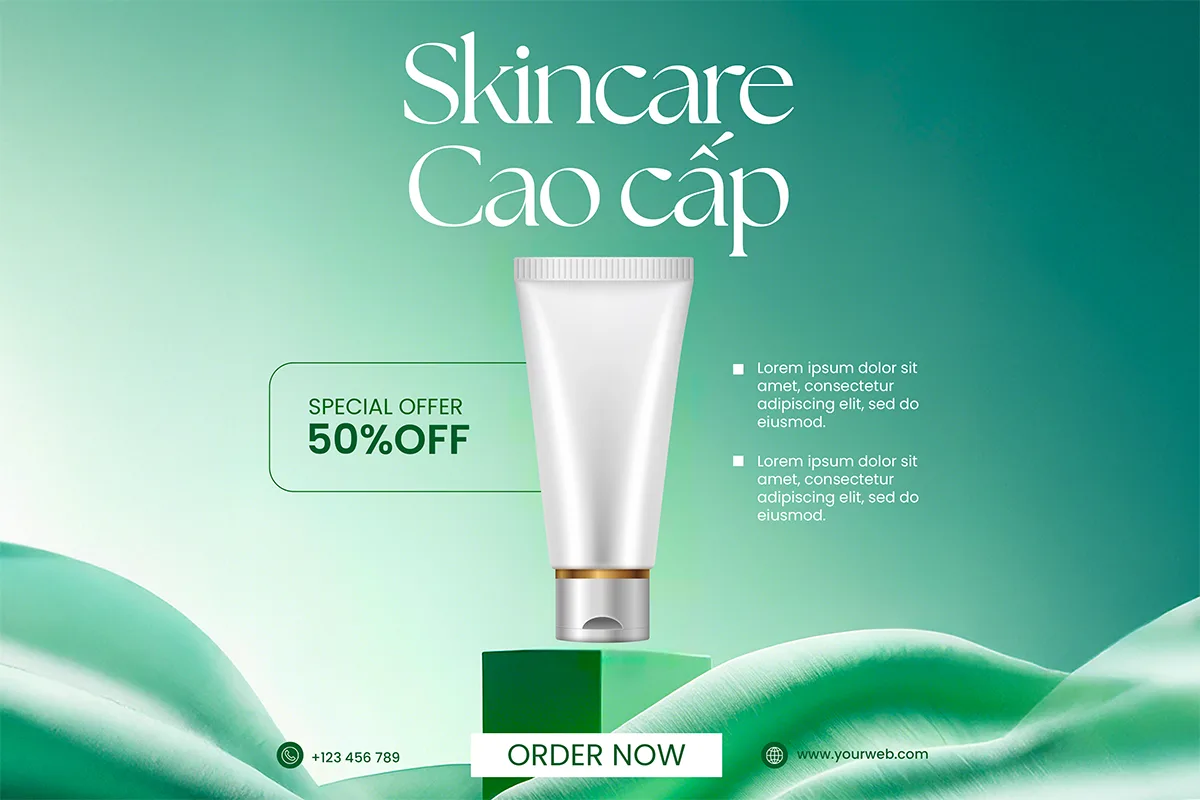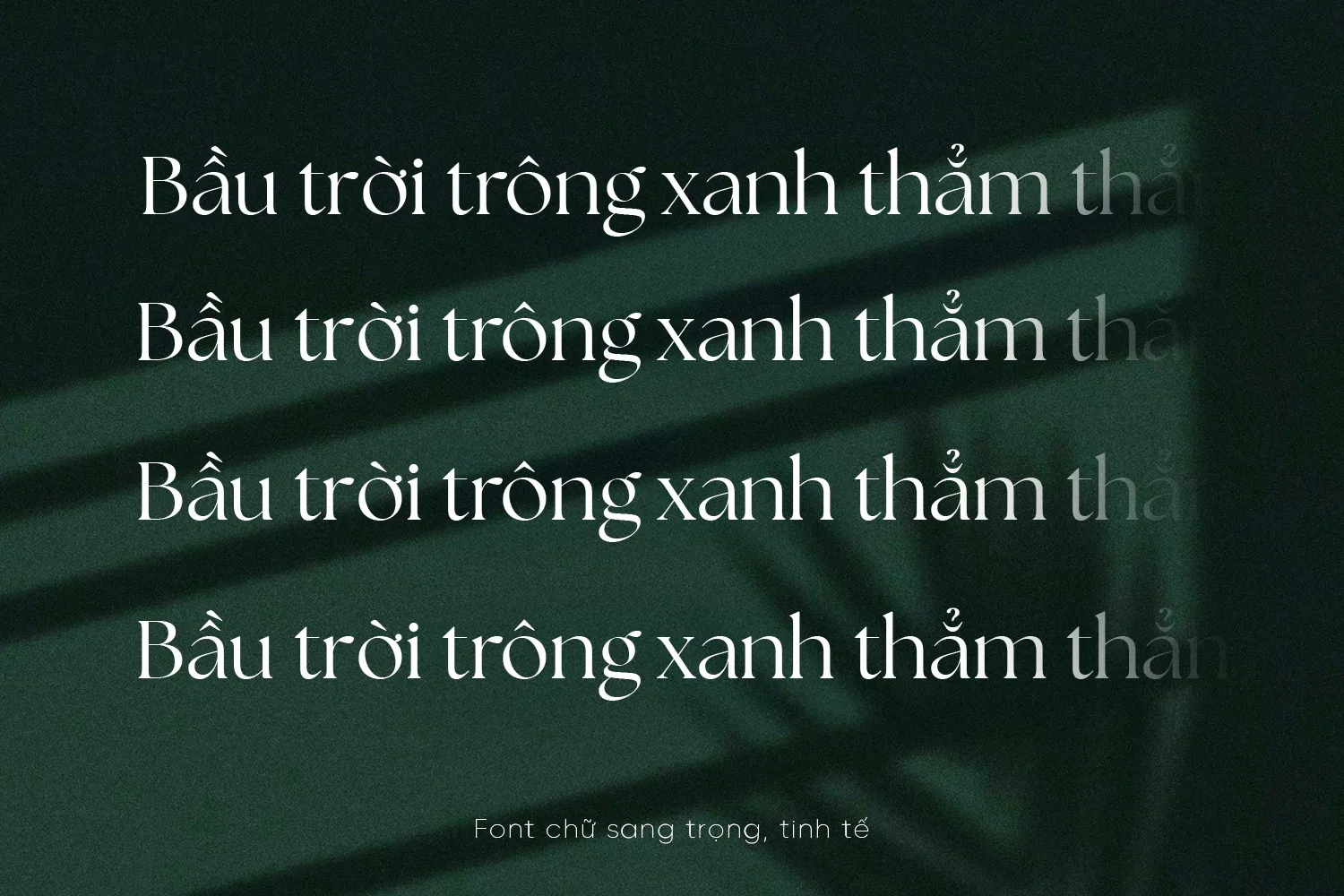
DVN The Seasons Việt hóa – Font chữ phù hợp cho thương hiệu sang trọng, mỹ phẩm
DVN The Seasons là một font serif mang phong cách sang trọng, tinh tế và hiện đại, được Việt hóa đầy đủ dấu tiếng Việt. Font sở hữu những đường nét thanh mảnh nhưng dứt khoát, kết hợp cùng chi tiết uốn lượn tinh xảo ở phần chữ cái, tạo cảm giác cao cấp và cuốn hút ngay từ cái nhìn đầu tiên.
Style Việt hóa: Regular
Đặc điểm nổi bật
Phong cách sang trọng: Thiết kế chữ serif cao và thanh thoát, phù hợp với các thương hiệu muốn thể hiện sự đẳng cấp.
Việt hóa hoàn chỉnh: Hỗ trợ đầy đủ dấu tiếng Việt, đảm bảo trải nghiệm nhất quán trong thiết kế.
Tính ứng dụng đa dạng: Thích hợp cho thiết kế logo, bao bì mỹ phẩm, nhãn chai rượu, thời trang cao cấp, và các ấn phẩm marketing yêu cầu sự tinh tế.
Hiệu ứng thị giác mạnh mẽ: Các chi tiết sắc nét giúp chữ nổi bật trên nền hình ảnh hoặc màu sắc đa dạng.
Gợi ý sử dụng
Thương hiệu mỹ phẩm & làm đẹp: tạo cảm giác tinh khiết, cao cấp.
Bao bì sản phẩm sang trọng: như rượu vang, nước hoa, trà thượng hạng.
Ấn phẩm thời trang: poster, lookbook, catalog cần sự thanh lịch.